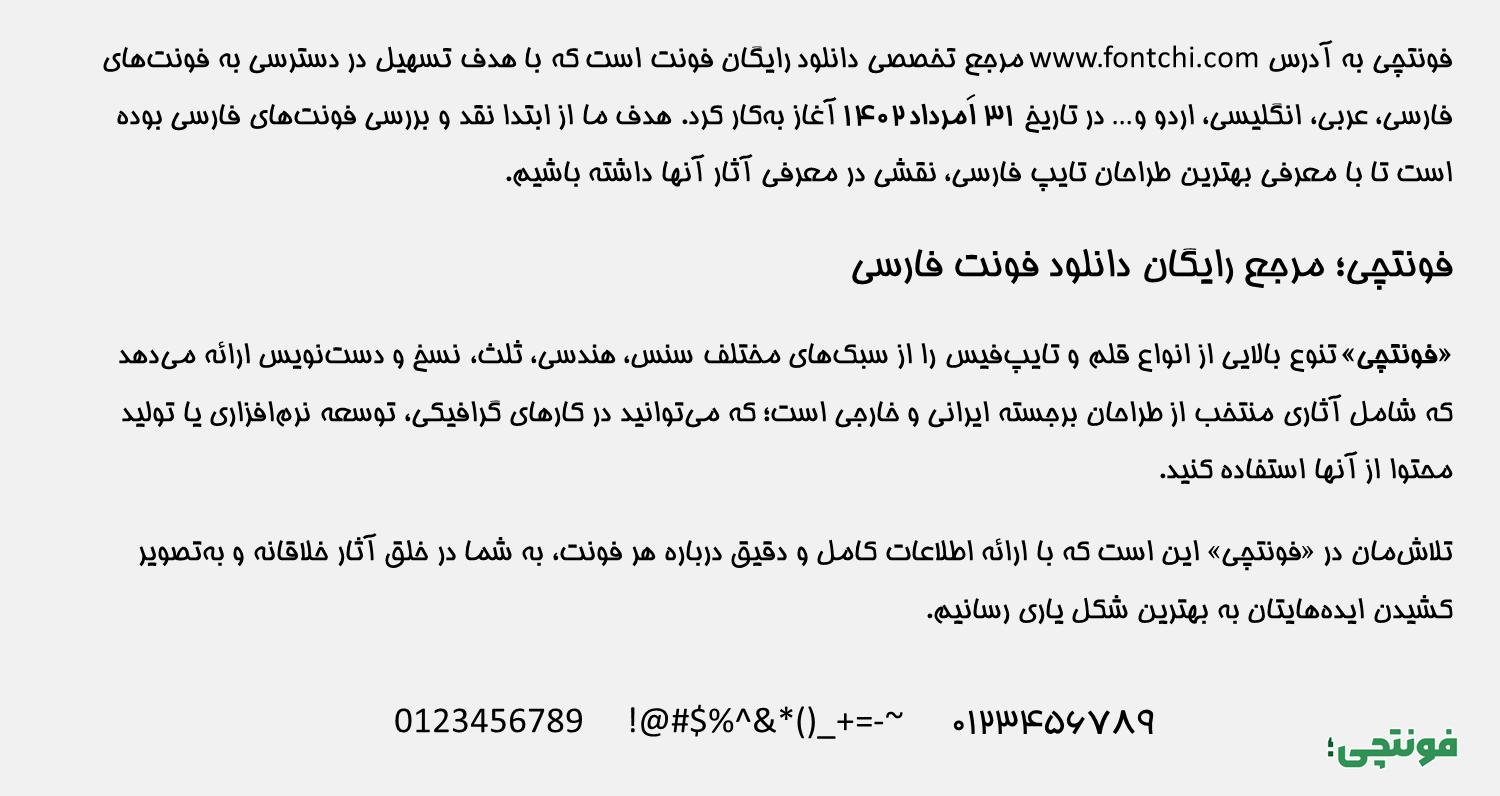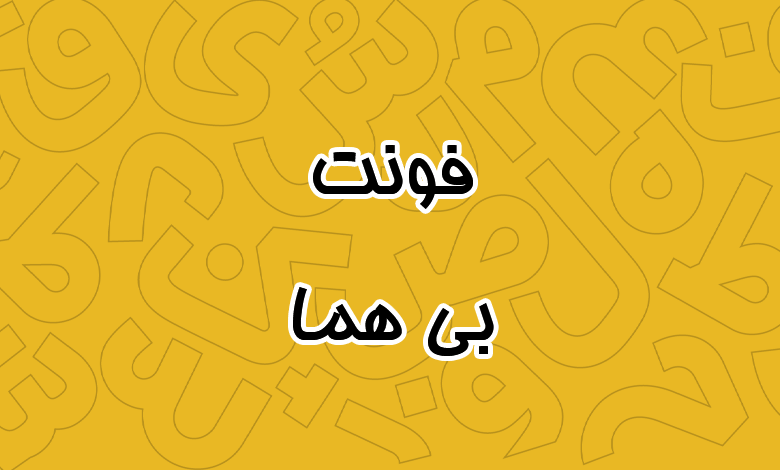
فونت بی هما (B Homa)
فونت بی هما (به انگلیسی: B Homa) قلمی فارسی از سری فونتهای B است که میتوانید از آن در متنهای کاملا فارسی استفاده کنید. این قلم که به سبک خط نسخ طراحی شده، برای استفاده در متون و عناوین میتواند مورد استفاده قرار گیرد. در ادامه به لینک دانلود فونت بی هما دسترسی خواهید داشت.
شرکت برنا رایانه این قلم را در کنار سایر قلمهای بی در دهه ۷۰ تولید کرده است که پشتیبانی کاملی از زبان فارسی و گلیفهای آن دارد. ساختار فونت طوری است که جنبه فانتزی داشته و میتواند برای موضوعات غیررسمی استفاده شود. از این فونت بیشتر در مطبوعات، تبلیغات و فونت عناوین کتاب استفاده شده است.
در ادامه این نوشته از سایت فونتچی به نقد و بررسی کامل فونت B homa خواهیم پرداخت که میتوانید با امکانات و ویژگیهای این قلم آشنا شده و با توجه به کارکردی که دارد در محیطهای مناسب از آن بهره ببرید.
پیش نمایش و وزن فونت بی هما (B Homa)
ساختار قلم بی هما غیر رسمی است؛ تا حدودی ظاهری فانتزی و نمایشی دارد که از همینرو بهترین کاربرد آن میتواند در حوزه تبلیغات یا استفاده به عنوان فونت کتاب و مجلات باشد. در این فونت از سبک نقطهگذاری پیوسته استفاده شده است که در دهه هفتاد استفاده از چنین سبکی در فونتهای دیجیتال مرسوم نبوده است.
ظاهر کلی حروف در این فونت دارای زاویهای نسبتا ایتالیک است که مشابه با فونت بی عرشیا در بخشهای مختلفی دارای ارتفاع خاصی هستند. دندانهها نسبت به حالت عادی خود ارتفاع بیشتری دارند، گردی حروفی همچون «ل، ن، ی، س» دارای عمق کمتر و چشمیها در حروفی مثل «ه، ص، ض، ـع» نیز دارای اندازههای متفاوتی هستند.
این فونت به صورت کامل از زبان فارسی پشتیبانی میکند که کلیه حروف فارسی را در کنار اعداد فارسی دارد. اما برخی کاراکترهای خاص که در تصویر زیر هم آن را میبینید فاقد گلیف بوده و از فونت پیشفرض سیستم عامل برای آنها استفاده میشود.
در فونت فارسی بی هما پشتیبانی از زبان انگلیسی وجود ندارد و فونت پیشفرض سیستم عامل هرچه باشد از آن استفاده خواهد شد. برای زبان عربی نیز گلیف جداگانه اختصاص داده نشده است؛ اما بهلطف یکسان بودن رسم خط فارسی و عربی میتوانید از حروفی که مشترک هستند برای زبان عربی استفاده کنید. ولی فراموش نکنید که حروفی مثل «ک، ی، ه، ؤ» یا اعداد عربی «۴۵۶» را ندارد.
بیشترین کاربردی که فونت بی هما دارد، در تبلیغات محیطی است. تراکتهایی که بهصورت روزمره در سطح شهر پخش میشوند، بیلبوردهای تبلیغاتی یا بستهبندی محصولات بخشی از این کاربردها هستند که همچنان از دهه هفتاد مورد استفاده قرار میگیرند.